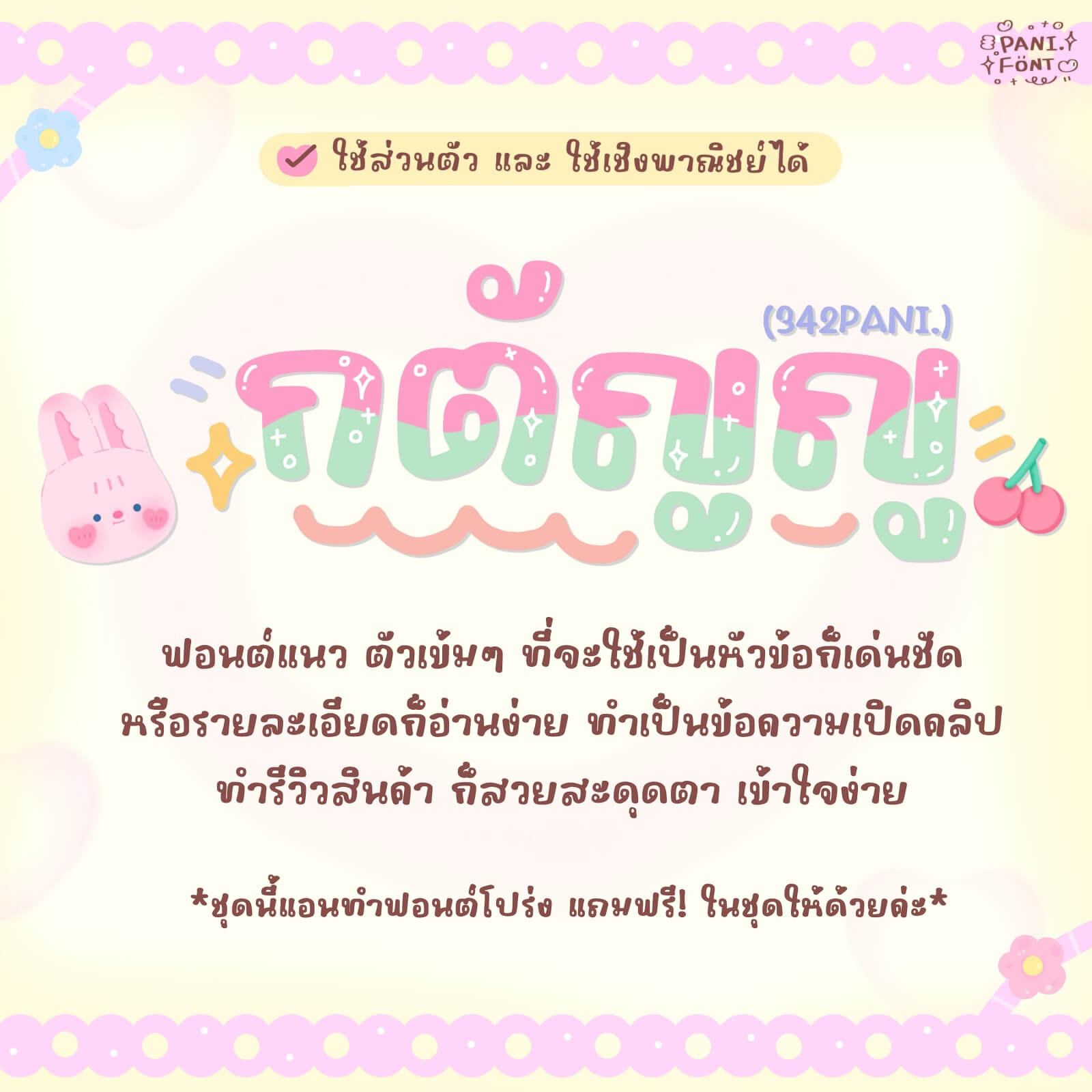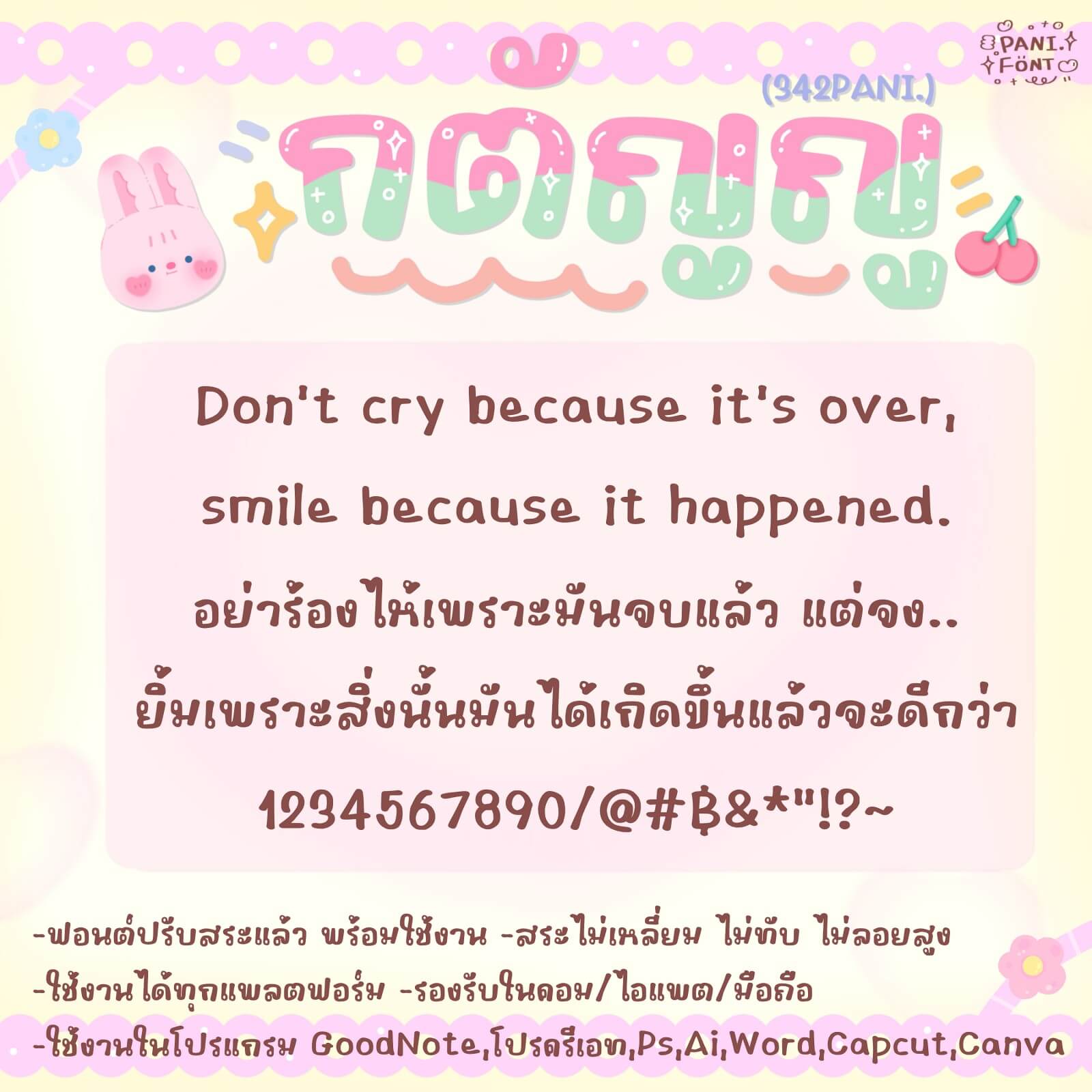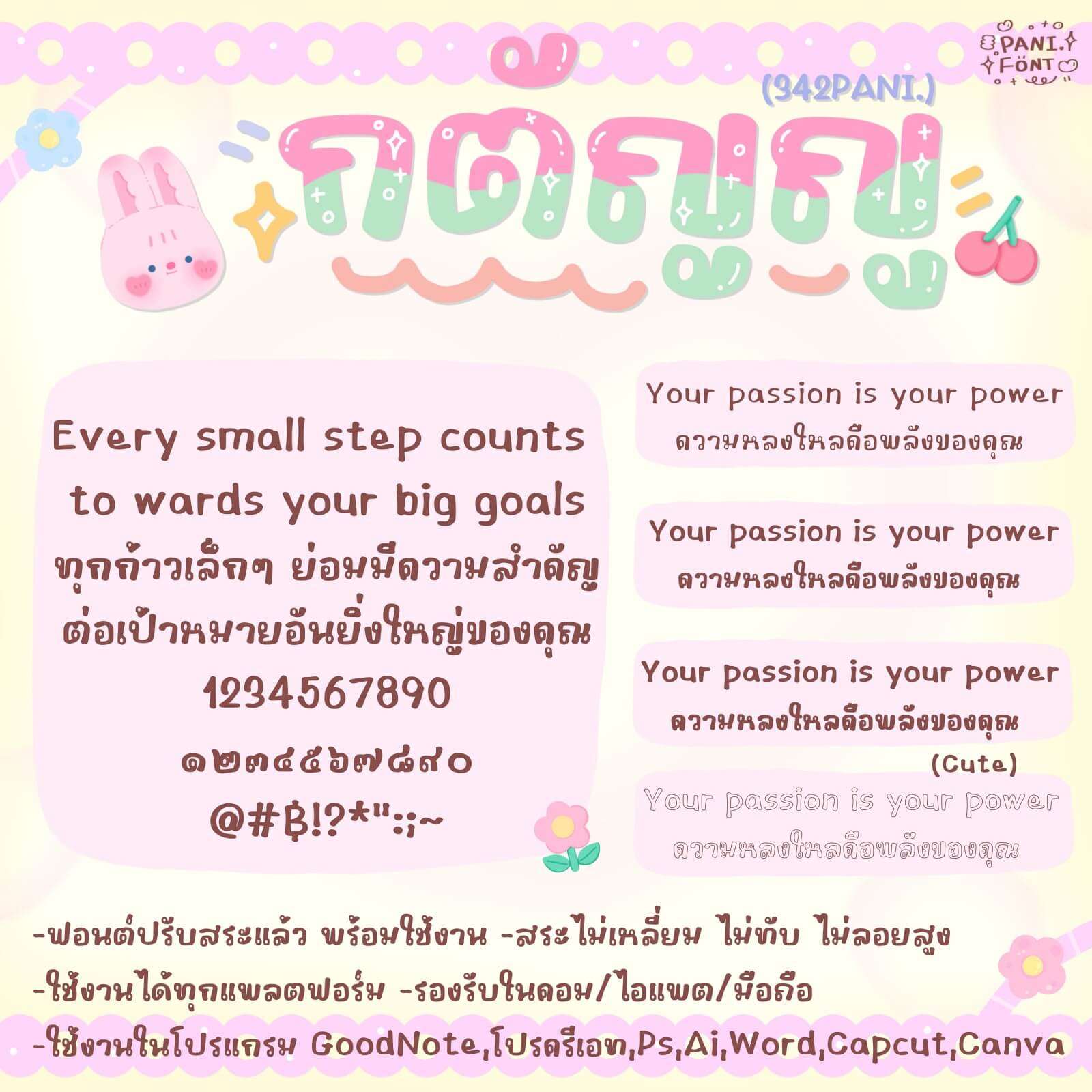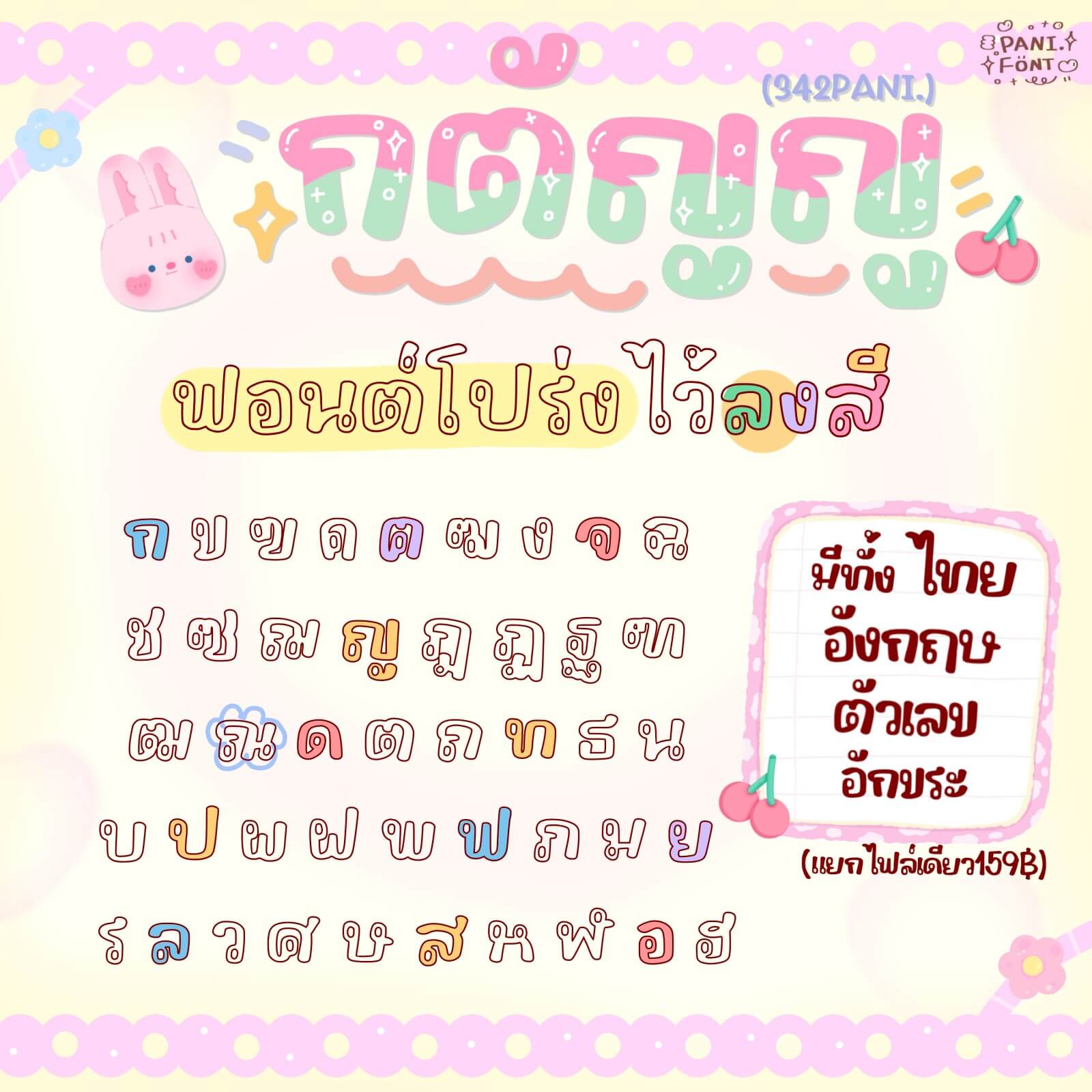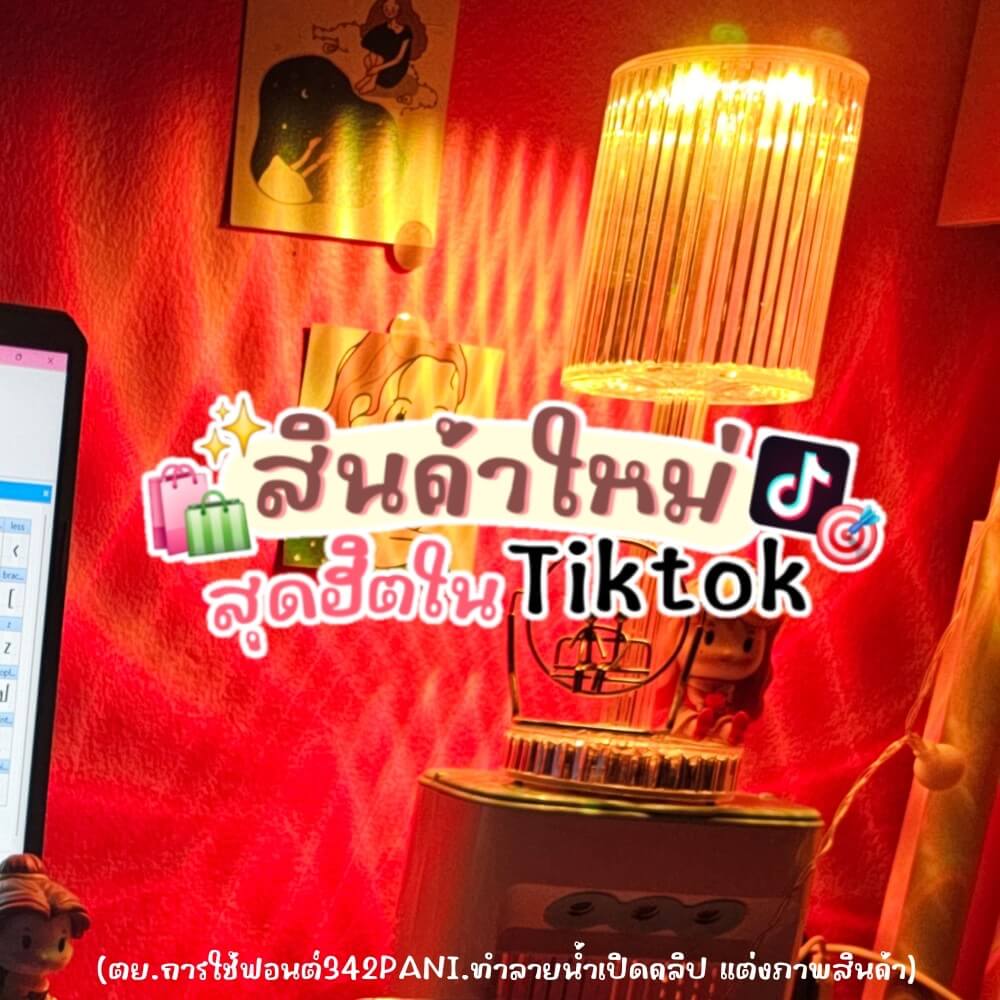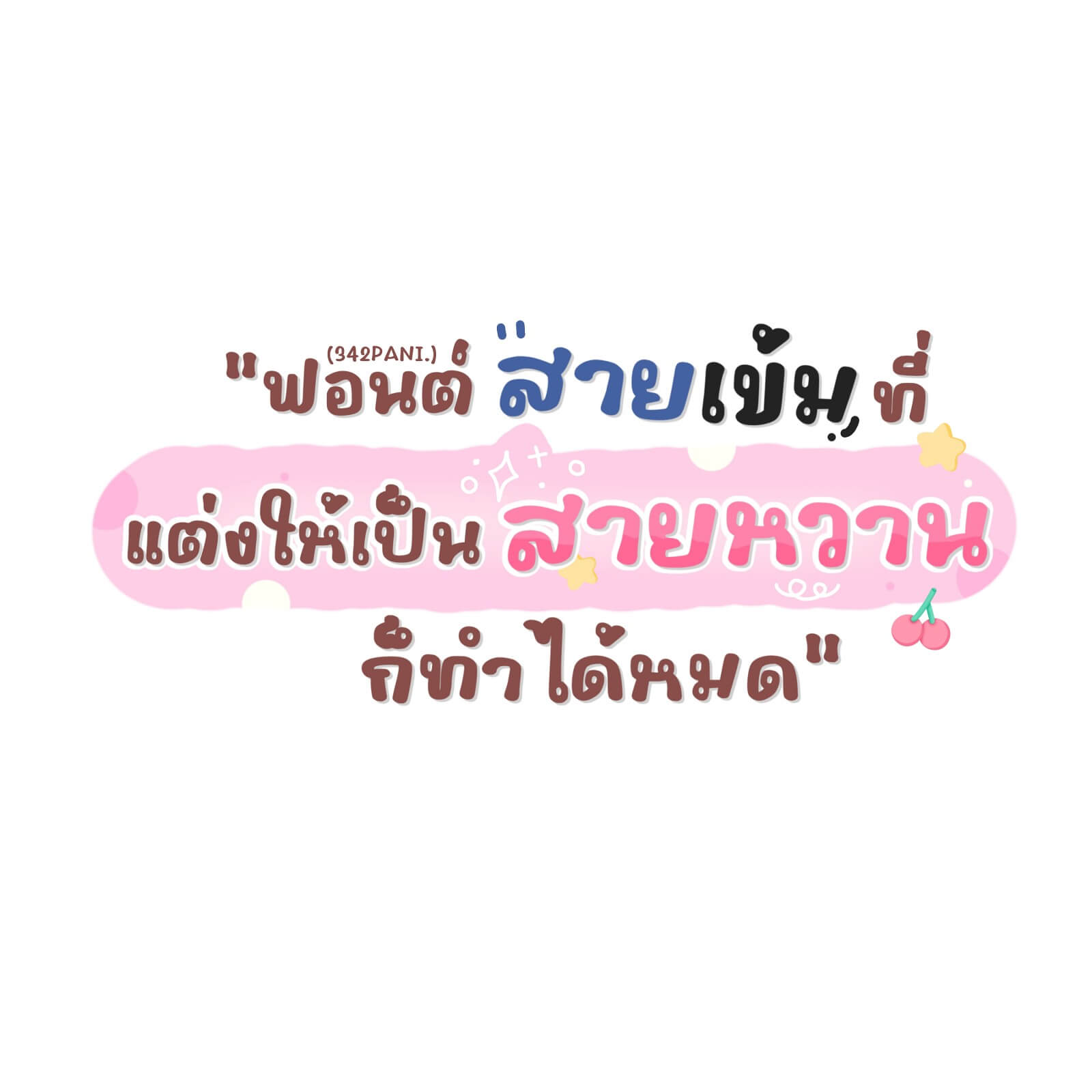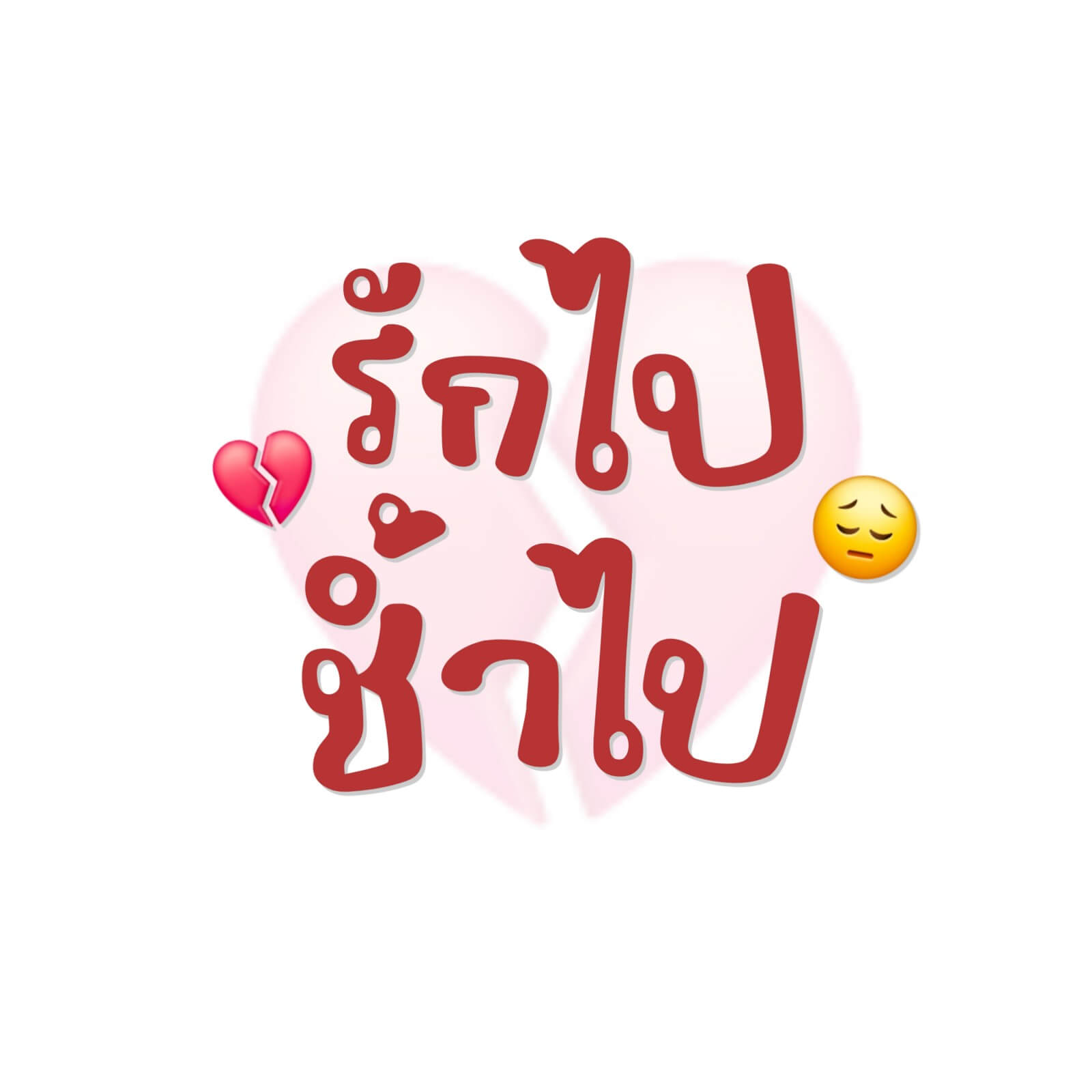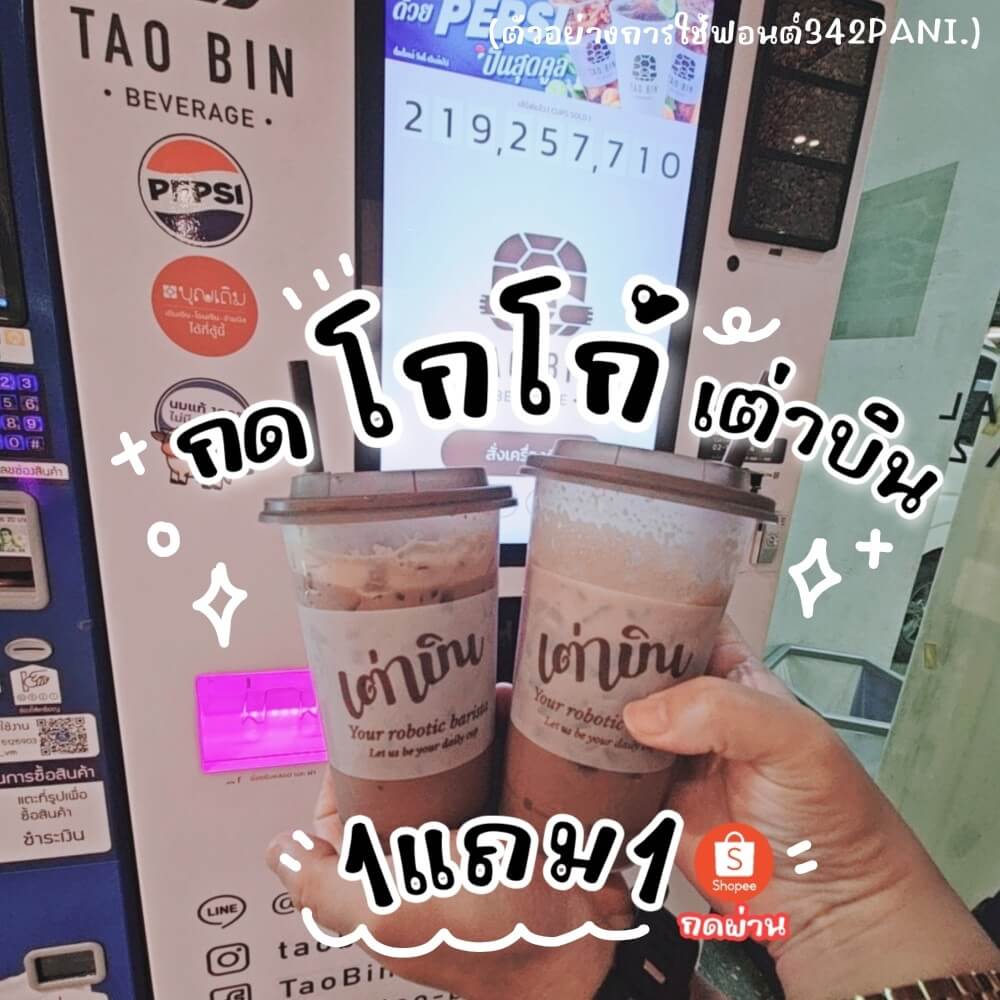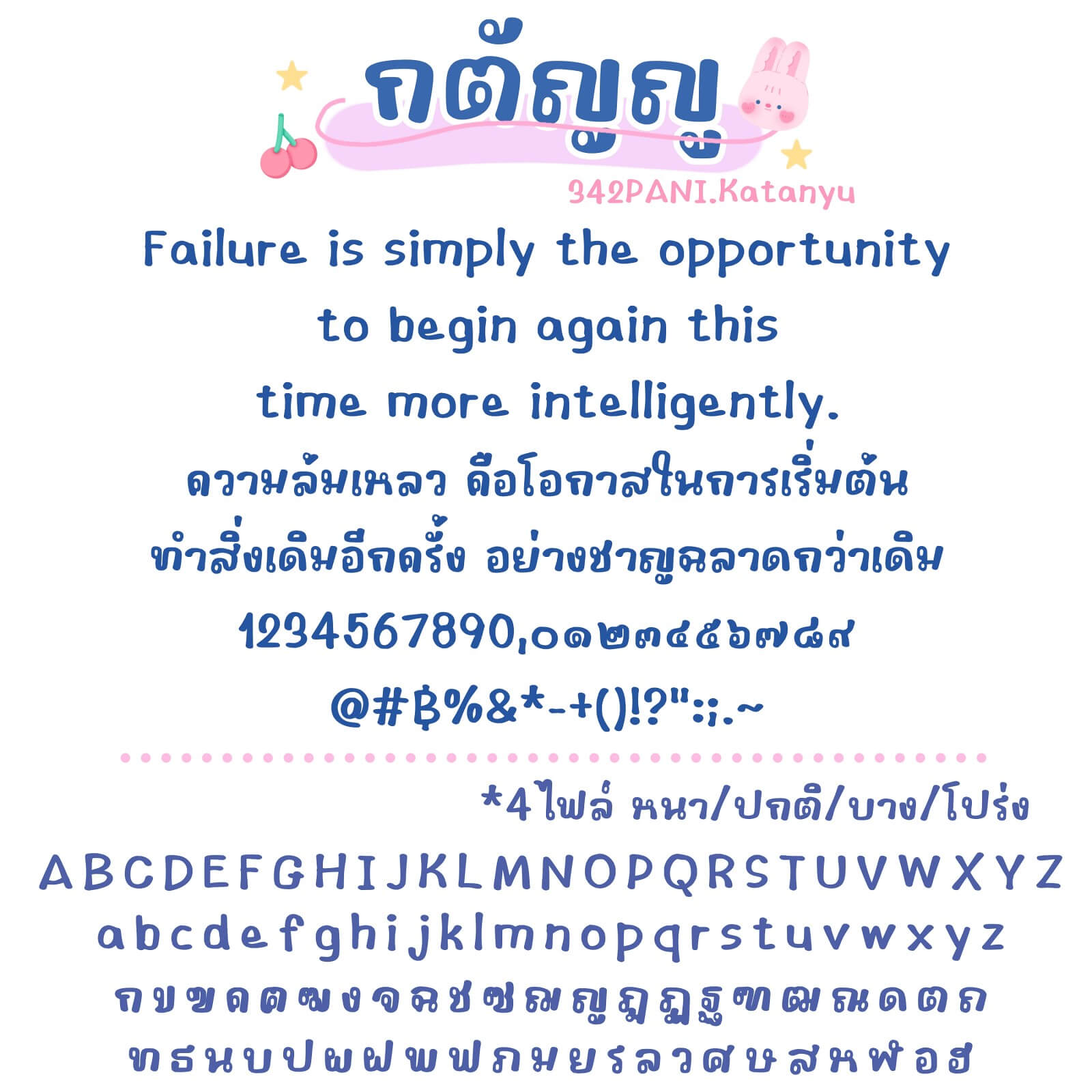
ฟอนต์ 342PANI.กตัญญู – โหลดทดลองใช้ฟรีตัว Demo ฟอนต์แนวตัวเข้มๆ ที่จะใช้เป็นหัวข้อก็เด่นชัด หรือรายละเอียดก็อ่านง่าย ทำเป็นข้อความเปิดคลิป ทำรีวิวสินค้า ก็สวยสะดุดตา ดูเข้าใจง่าย
342PANI.กตัญญู